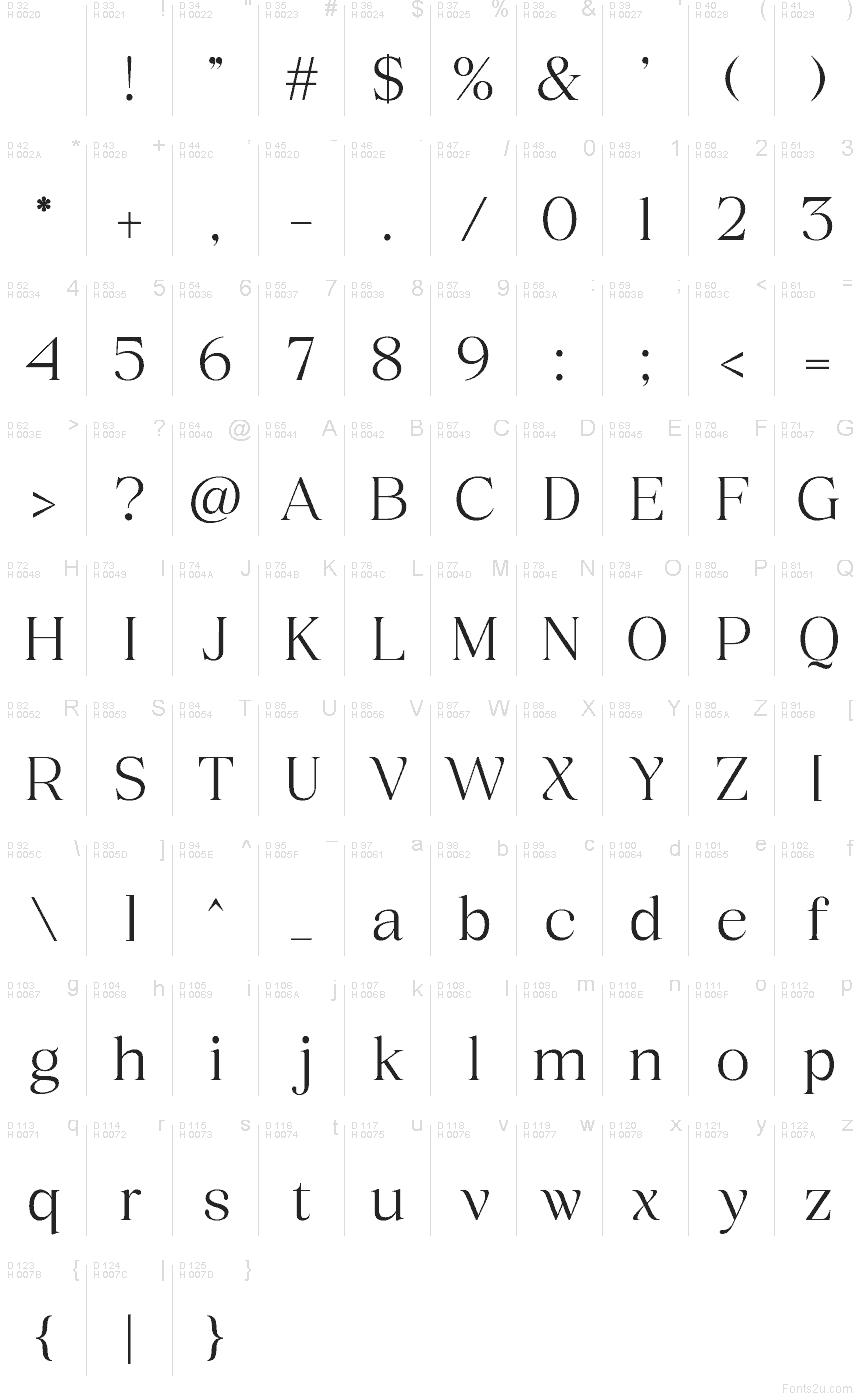
Scaver Extra Light di Glyphminds Studios è un carattere con grazie ad alto contrasto, gratuito e con un'estetica editoriale e alla moda. Le lettere uniscono tratti sottilissimi a curve ampie e sinuose, mentre le terminazioni appuntite, dal tocco leggermente calligrafico, conferiscono un'eleganza che non risulta mai fredda o meccanica.
Questo font gratuito si adatta perfettamente a testate di riviste, packaging di prodotti cosmetici, branding di boutique, copertine di libri e poster di gallerie dove è richiesta una voce raffinata. È particolarmente indicato per titoli brevi e cartoline, dove le sue curve lunghe e il contrasto nitido donano a ogni parola una presenza distinta e curata.